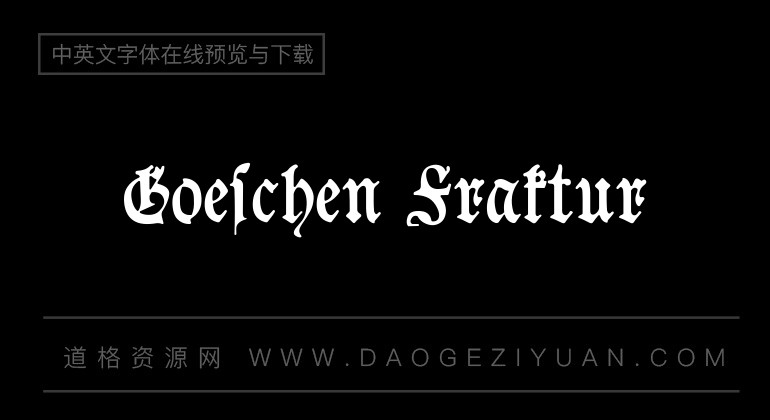
Goeschen Fraktur是一种黑体字体,属于德国黑体字体的分支之一,于1913年由德国打字机制造商Goeschen公司推出,可以追溯到德国文艺复兴时期的手写书法。它的特点是通过使用断笔的方式,使字母线条产生细微变化,呈现出非常独特的传统德国手写书法风格。 Goeschen Fraktur字体在其创造时期非常受欢迎,因为它被认为是一种非常清晰易读的字体,同时也具有很高的美学价值。然而,在第一次世界大战期间,德国政府禁止使用Fraktur字体,因此它的使用逐渐减少,直到今天只在一些特殊场合使用。 总的来说,Goeschen Fraktur是一种非常有趣和独特的字体,展现了德国手写书法的传统特色。内容介绍
Goeschen Fraktur是一款非常不错的手写艺术字体,具有很好的视觉感,适合于文化类的宣传设计、商业类品牌的广告和产品包装设计以及个性化文字排版等较多场景。